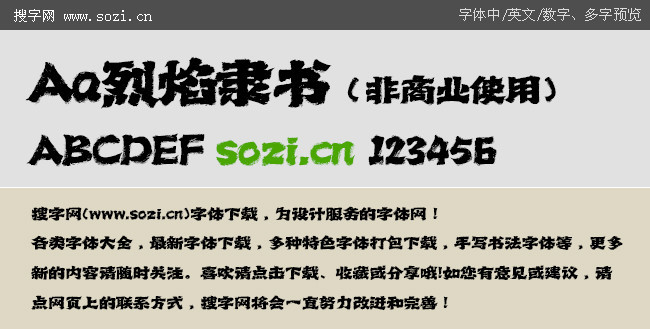
Aa烈焰隸書
搜字網(wǎng)給大家提供一款A(yù)a烈焰隸書(非商業(yè)使用)中文字體下載,該字體是一款中文藝術(shù)字體,風(fēng)格比一般的字體更有特色,具有很好的視覺感,適合書裝設(shè)計、包裝、海報設(shè)計等應(yīng)用(此字體為個人非商用版,商用可以聯(lián)系QQ:1006760504)。